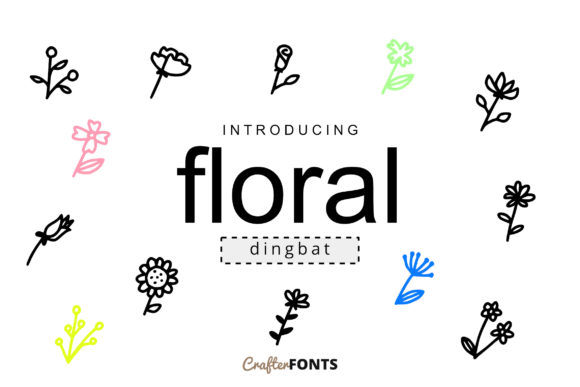
Floral Doodle
適切なデザイン要素を見つけるのは難しい場合がありますが、Floral Doodleは作品を即座に引き立てる優れたコレクションを提供します。
POD(オンデマンド印刷)製品、結婚式の招待状、またはソーシャルメディアのグラフィックを作成している場合でも、Floral Doodleは理想的です。